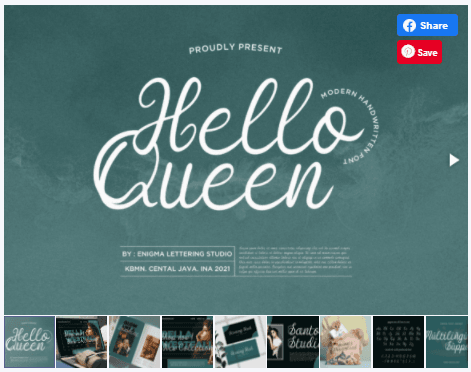
Hello Queen Font
Hello Queen - прекрасный и тонкий шрифт, излучающий элегантность и класс. Этот шрифт был специально разработан для тех, кому нужен красивый и освежающий вид своего дизайна.